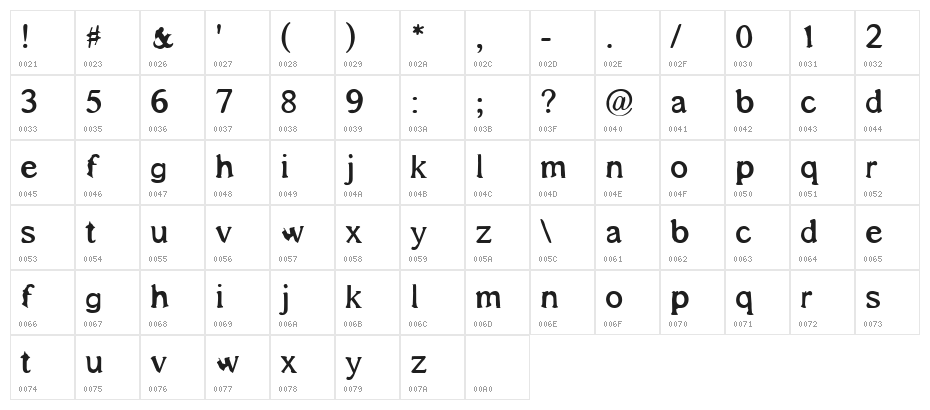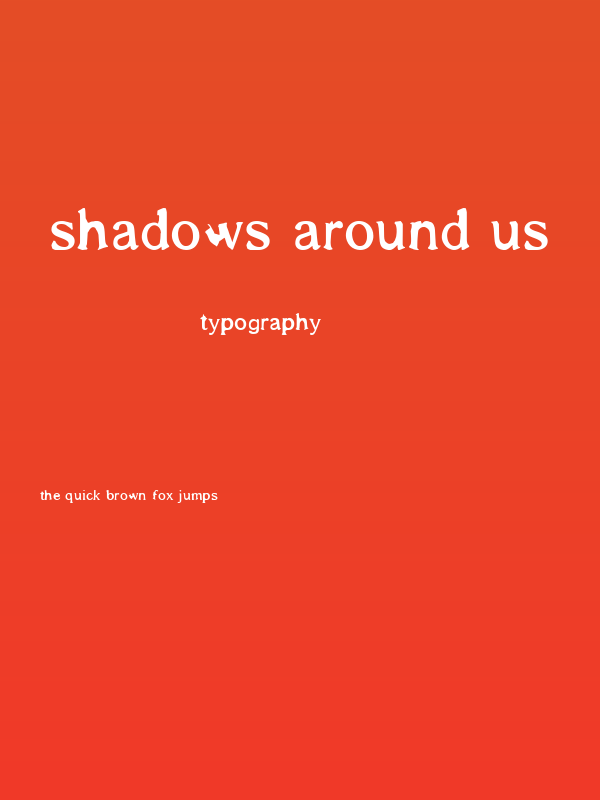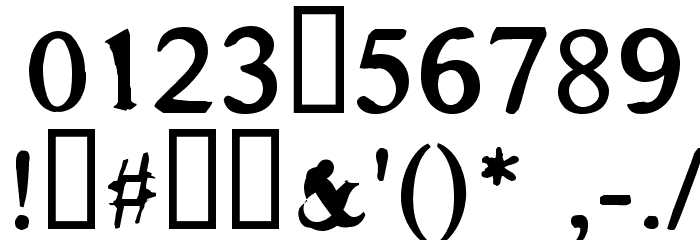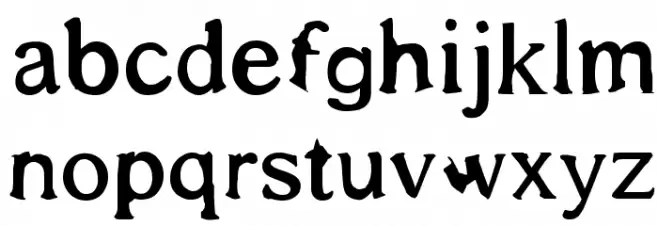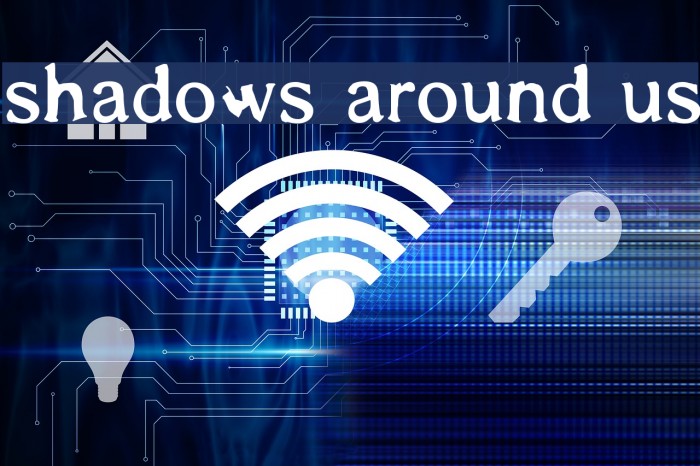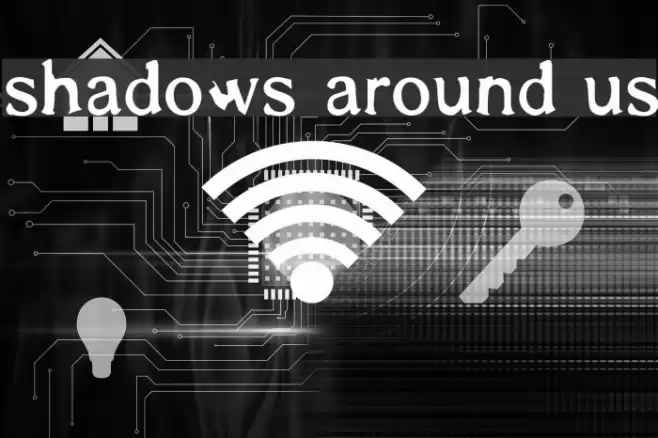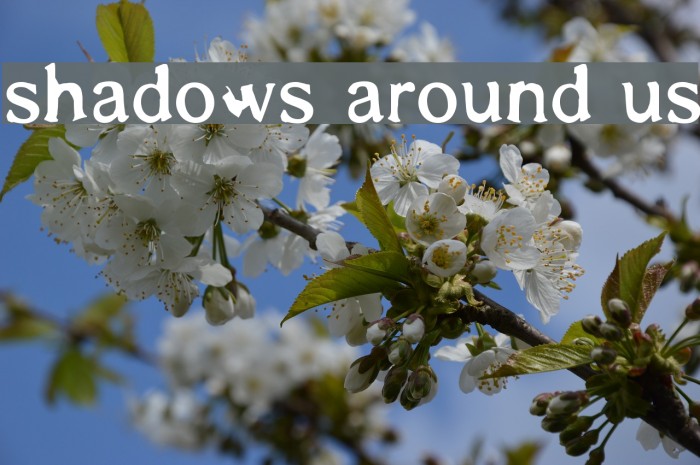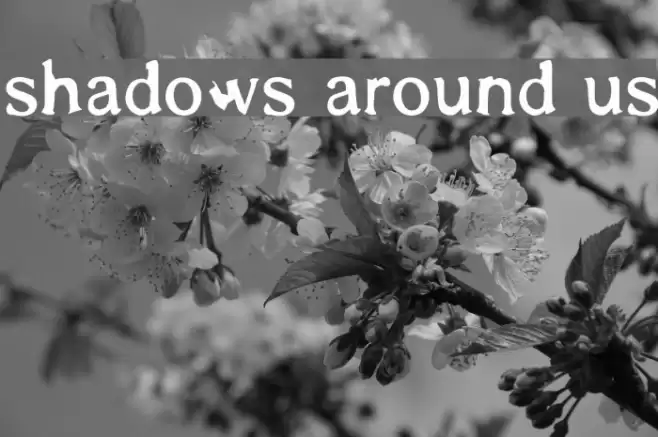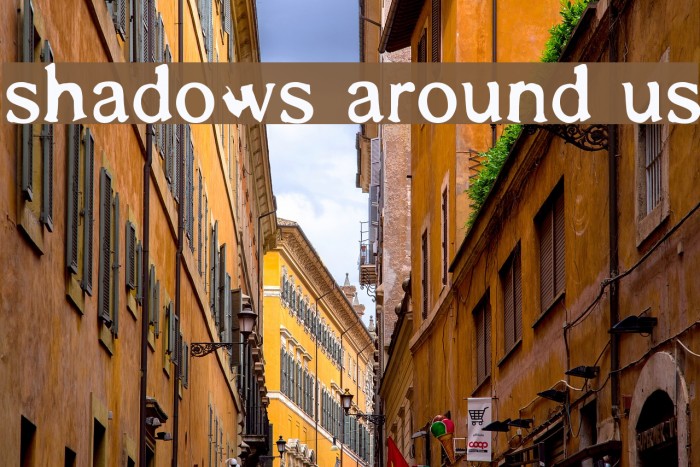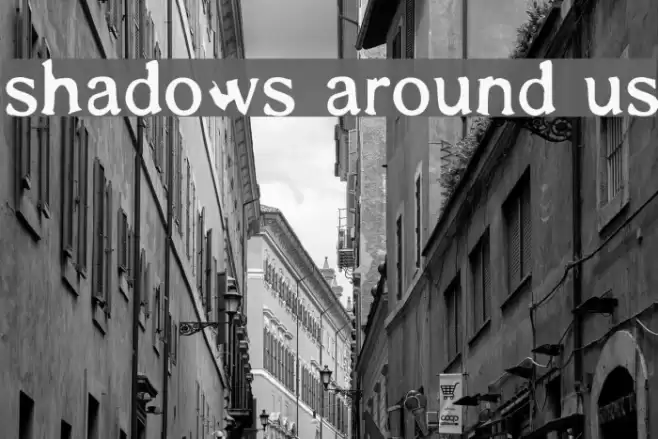
Shadows Around Us Font
| Vorgeschlagene Projekte | Ideal for book covers, posters, branding projects, and any design requiring a touch of elegance and creativity. |